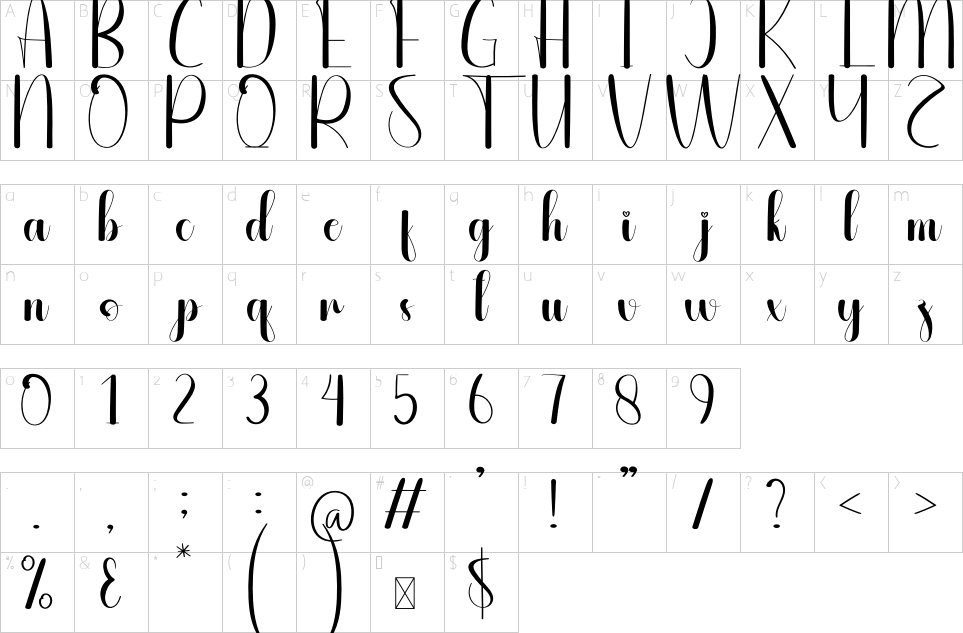
Descubra uma nova fonte chamada Sample Font, disponível para download gratuitamente. Esta fonte foi criada por um designer não informado e tem sido baixada 401 vezes, mostrando o seu valor e popularidade. Se você está buscando uma fonte moderna e fácil de ler, Sample Font é uma ótima escolha para seu próximo projeto. Seja para uso em seu site, aplicativos ou até mesmo para criar flyers e cartazes, esta fonte oferece uma variedade de opções para personalizar seu layout. Com seu design limpo e elegante, Sample Font é perfeita para criar um visual profissional e agradável para o seu trabalho. Não deixe de baixar agora e dê uma nova cara a seu design.